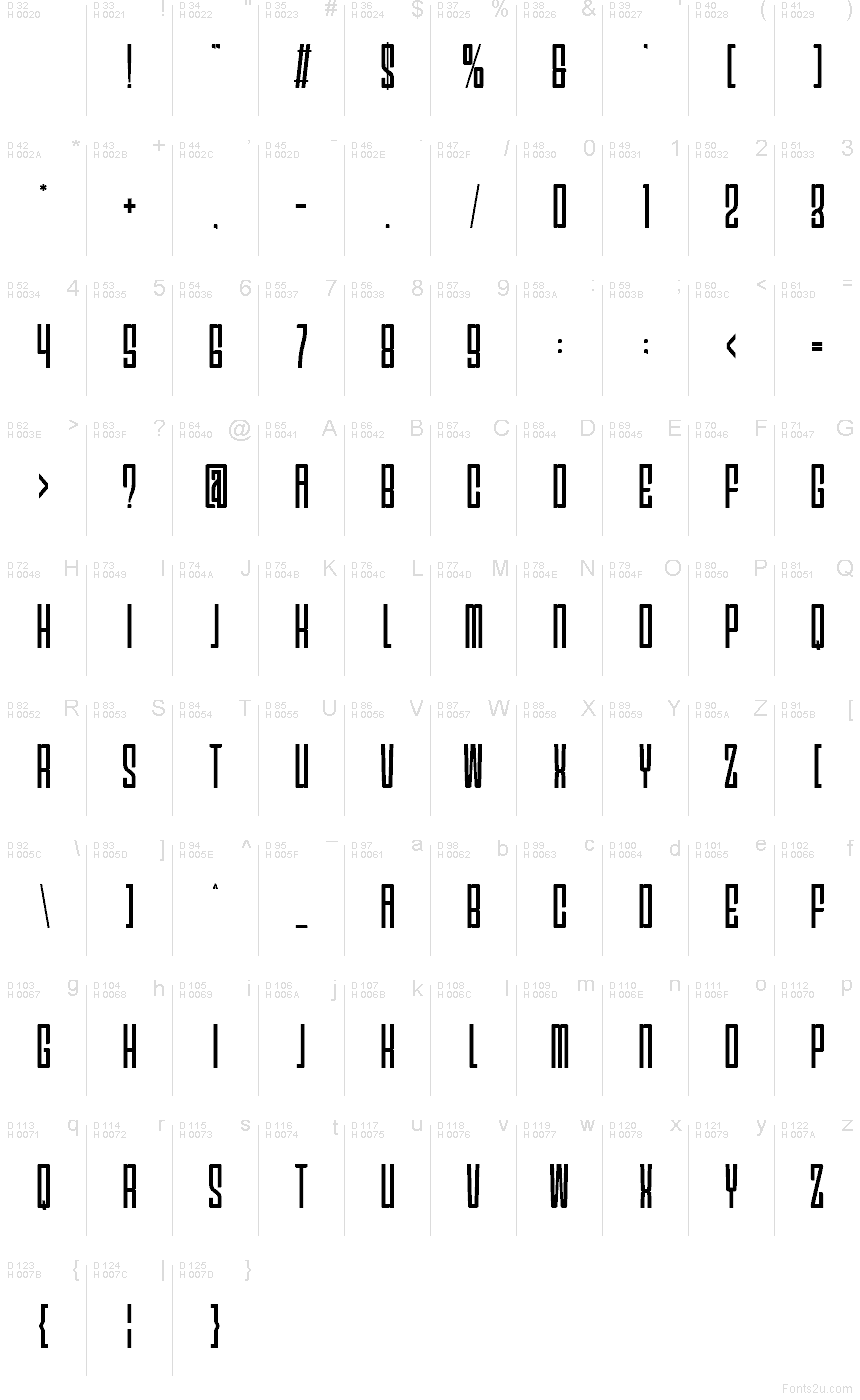
Aminoke de Ermedia Studio es una tipografía display techno gratuita y ultracondensada, caracterizada por un marcado énfasis vertical y una silueta severa y estructurada. Sus imponentes mayúsculas combinan trazos anchos y uniformes con contraformas estrechas a modo de rendijas, mientras que las curvas cuadradas y las uniones abruptas en ángulo recto aportan a las letras un aspecto de corte mecánico.
Funciona especialmente bien en carteles de música electrónica, donde sus estrechas proporciones permiten destacar el título de un evento con gran impacto en un ancho limitado. Esa geometría industrial también encaja en pantallas de títulos de videojuegos y empaques futuristas. En el diseño de marcas de moda y gráficos digitales, la repetición de las barras verticales puede transformarse en un patrón arquitectónico o en un panel de interfaz, convirtiendo el propio rótulo en parte de la imagen.